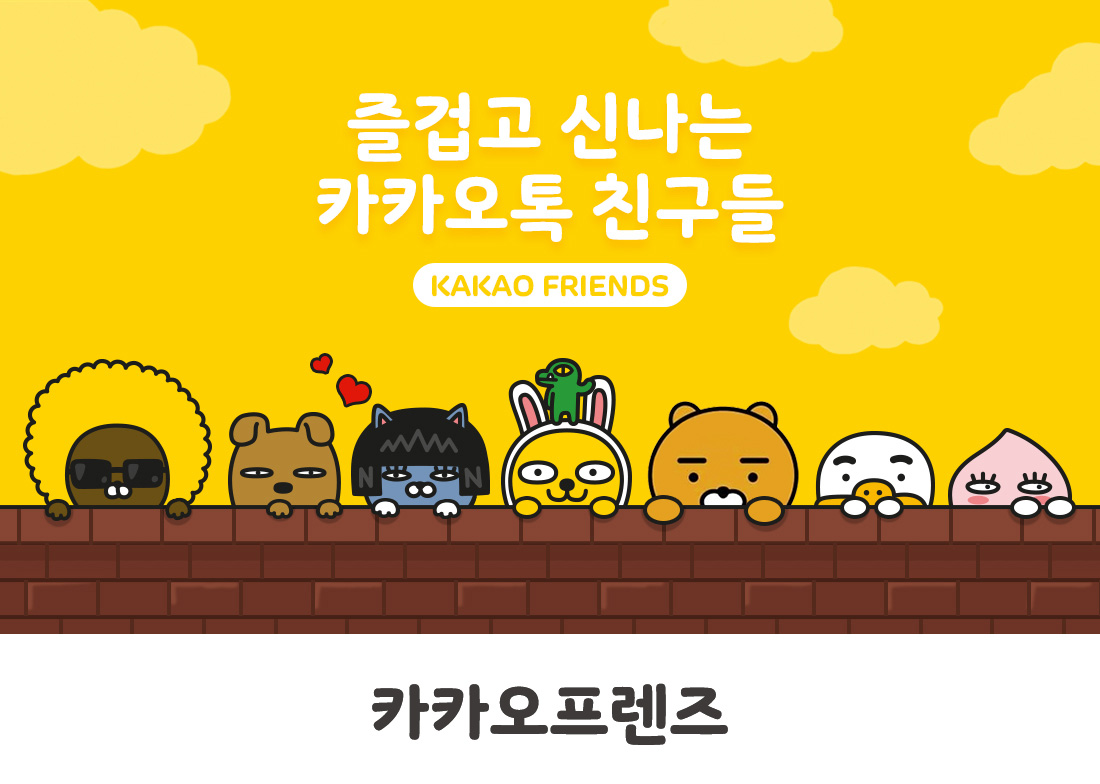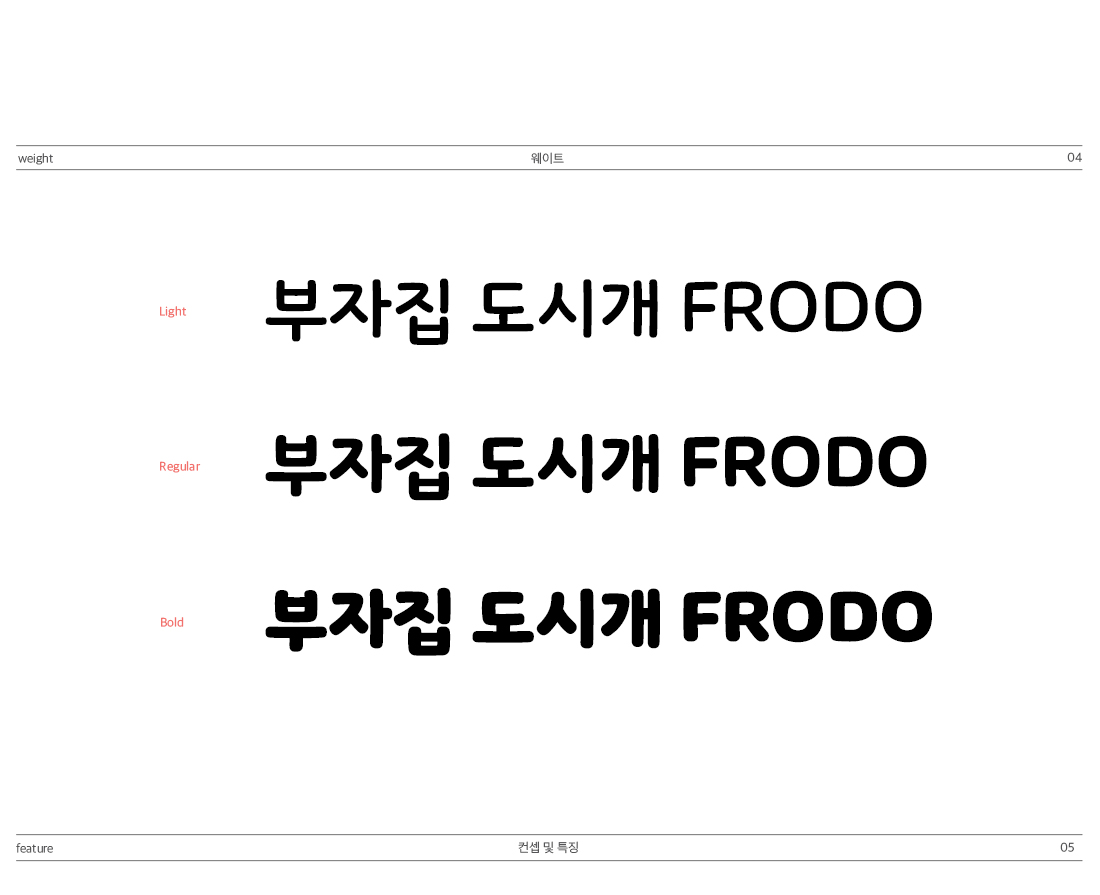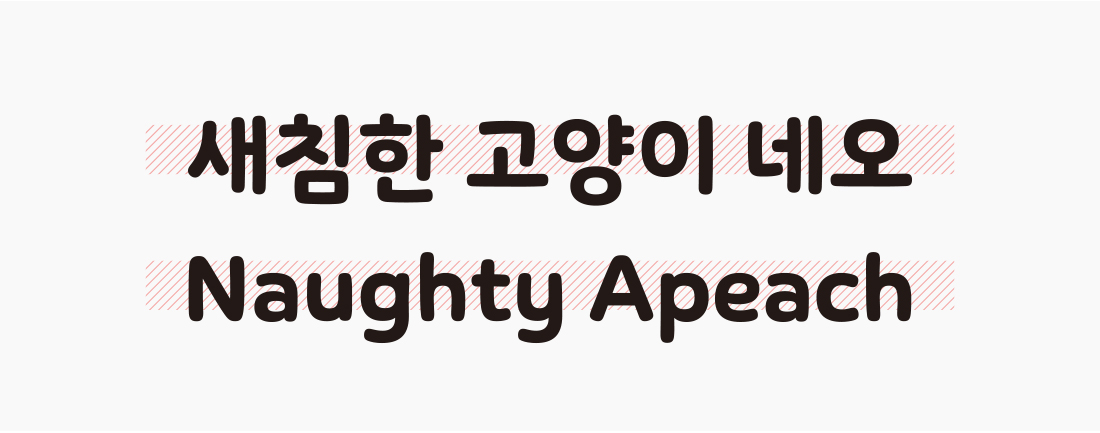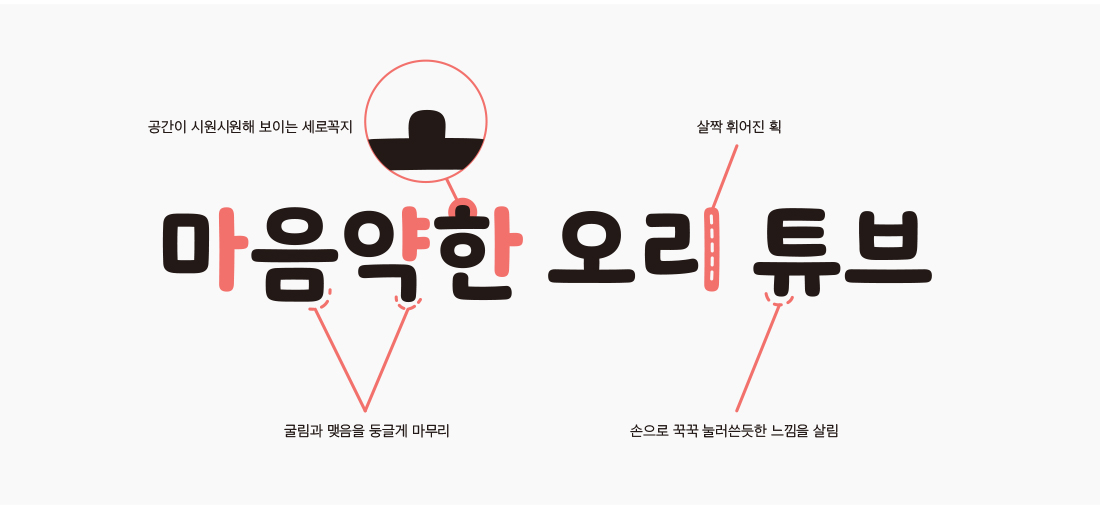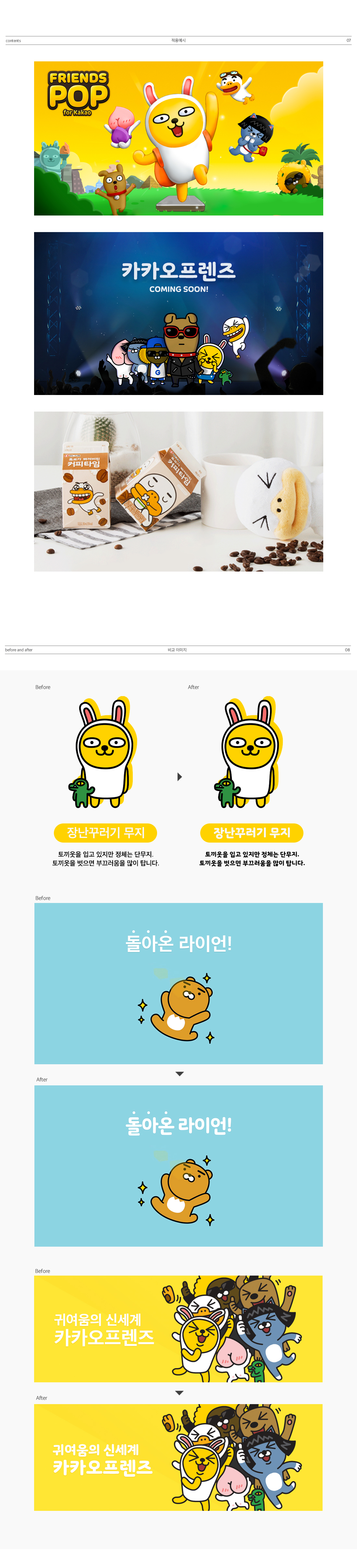
카카오프렌즈 전용서체 : 즐겁고 신나는 카카오톡 친구들
타이포브랜딩 : 카카오프렌즈 전용서체
제이지, 프로도, 네오, 무지, 콘, 라이언, 튜브, 어피치.
이제는 너무나 친근해져버린 국민 이모티콘, 카카오프렌즈. 카카오톡의 마스코트로써 이들이 지닌 개성 만점의 캐릭터를 더욱 잘 표현하고, 일관된 아이덴티티로 커뮤니케이션하기 위해 카카오프렌즈만의 전용서체를 제작하게 되었다.
제작배경
카카오프렌즈의 인기가 날로 높아지자 카카오에서는 카카오프렌즈를 독립법인으로 분사하였고, 카카오프렌즈만의 아이덴티티를 강화하기 위해 전용서체 제작을 의뢰하였다. 마냥 귀엽다기보다는 다소 엉뚱하고 키치한 감성을 가진 캐릭터의 특징을 그대로 살리면서도, 가독성과 사용성이 좋은 폰트를 만드는 것이 가장 중요한 미션이었다.
디자인 과정
가장 중요한 것은 폰트와 카카오프렌즈 캐릭터와의 싱크로율이었다. 폰트와 캐릭터가 함께 보여지는 경우가 대부분이기 때문에 서로 잘 어울리는지 계속 확인하면서 작업했다.
카카오프렌즈는 ‘키치(kitsch)’라는 키워드로 표현되는데, ‘키치’란 아주 다양하게 해석될 수 있지만 ‘누구나 즐길 수 있다’는 것이 가장 중요하다고 생각했다. 이를 반영해 누구나 친근하게 느낄 수 있도록 자소를 약간 어설프면서 발랄한 느낌이 들도록 디자인했다.
하지만 가독성도 놓칠 수 없는 중요한 부분이어서, 단단하고 정돈된 모듈을 사용하는 등 중간지점을 찾기 위해 노력했다.
컨셉 및 특징
카카오프렌즈의 키치한 감성을 녹여낸 싱크로 200% 손글씨!
#개성넘치면서도 정돈된
개성넘치고 키치한 느낌을 주면서도 가독성을 해치지 않도록 안정적인 모듈을 사용했고 시각중심선이 살짝 위쪽으로 위치하여 글줄이 더 정돈되어 보이도록 한다.
#획 하나하나 손글씨 특징을 살린
글자의 굴림과 맺음을 둥글게 마무리하고, 획도 직선처럼 보이지만 살짝 휘어지게 표현했다. 전체적으로는 손으로 꾹꾹 눌러쓴 듯한 느낌을 살려 디자인했다.
비하인드 스토리
카카오프렌즈 전용서체는 프로젝트의 컨셉 자체가 엉뚱하고 키치해서 그런지 기존의 다른 전용서체에 비해서 좀 더 즐거운 마음으로 작업했다.
자료나 보고서를 만들 때도 캐릭터 이미지를 넣기도 할 만큼 캐주얼한 분위기였고, 그래서 카카오프렌즈 캐릭터를 조사하고 분석하는 일이 다른 사람에게는 노는 것처럼 보였을 수도 있을 것 같다.
작업하면서 까다로웠던 점은, 폰트 자체가 획이 두꺼운 편이라 Regular가 일반 서체의 Bold ~ Extrabold 두께에 가깝고 더 두꺼운 Bold는 정말 굉장히 굵다. 그래서 공간의 분배가 쉽지 않았다.
국문 폰트명 : 카카오프렌즈
영문 폰트명 : KAKAOFRIENDS
웨이트 : 3종(Bold/Regular/Light)
글자 구성 : 한글 11,172자 / 영문 / 약물